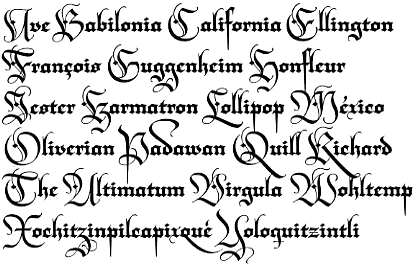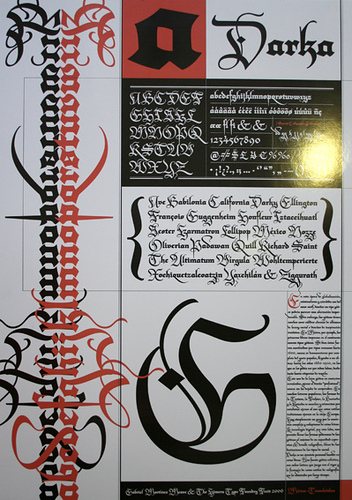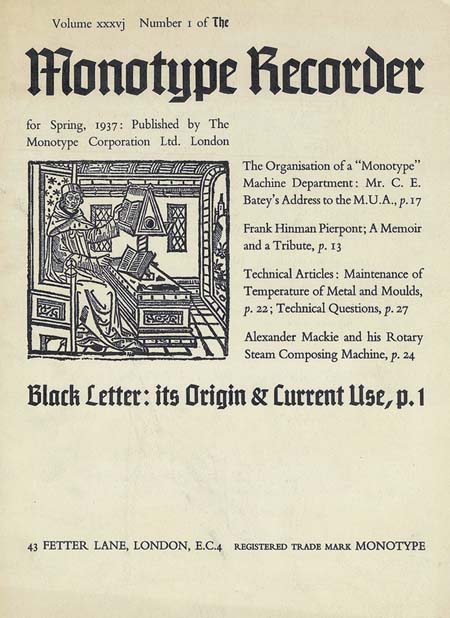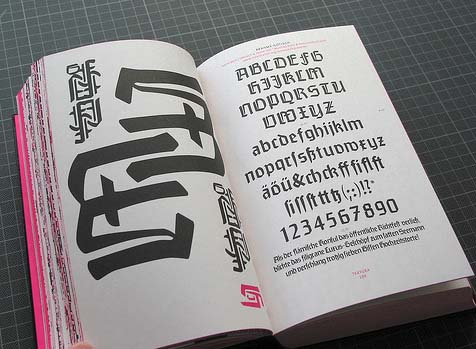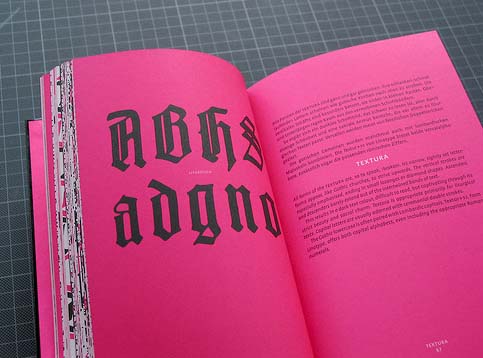
Fraktur - revivalismo
O Blackletter Revival: a Fraktur pelos quatro cantos do mundo...
A Blackletter sempre teve o seu protagonismo no mundo tipográfico britânico...
Blackletter Monotype Recorder
Monotype Recorder, 1937, sobre o uso da Blackletter
Nos últimos anos, temos assitido a um verdadeiro revivalismo da letra Fraktur. Especialmente devido a impulsos oriundos dos EUA e do México. Diseño Kimera propõe a fonte Darka - uma bela reincarnação da velha Fraktur no Novo Mundo:
Fraktur mon amour
Judith Schalansky. Fraktur mon Amour. 648 Seiten mit über 300 Frakturzeichensätzen und Schmuckbuchstaben aus insgesamt 644 Fonts
Como usar fontes Fraktur?
Bibliografia
• Anderlind, J. Deutschschrift, nicht Lateinschrift dem deutschen Volke. Berlin, 1911. Polémica pró-Fraktur, de cariz nacionalista.
• Brage, Hermann. Geschichte der Buchdruckerkunst. Leipzig, 1940. História da Imprensa.
• Bauer, Konrad F. Zur Geschichte der Unger-Fraktur. Gutenberg Jahrbuch, 1929.
• — Leonhard Wagner, der Schöpfer der Fraktur. Ein Beitrag zur Geschichte der deutschen Schrift. Frankfurt / Main, 1936.
• — Von der Zukunft der Schrift. Frankfurt / Main, 1966.
• Bissels, Paul. Humanismus und Buchdruck. Nieuwkorp, 1965.
• Chappel, Warren. A Short Story of the Printed Word. New York, 1970.
• Clauss, H. Die Schwabacher Schrift in Vergangenheit und Gegenwart. Leipzig, 1916.
• Crous, Ernst. Dürer und die Schrift. Berlin, 1923.
• Doede, Werner. Schön schreiben, eine Kunst. Johann Neudörffer und seine Schule im 16. und 17. Jahrhundert. München 1957.
• Ehmcke, Fritz Helmuth. Die drei Ausdrucksformen der deutschen Schrift: Textur - Schwabacher - Fraktur. Leipzig, 1912.
• Flood, J.L. Nationalistic currents in early German typography. The Library, 6a série, 15, 2, pp. 125-41. 1993.
• Fichtenau, Heinrich. Mensch und Schrift im Mittelalter. Wien, 1946. Grafias medievais.
• — Die Lehrbücher Maximilians I und die Anfänge der Frakturschrift. Hamburg, 1961.
• Franck, Paul. Schatzkammer allerhand Versalien, Nürnberg, 1601.
• Fugger, Wolfgang. Ein nützlich und wolgegrundt Formular manncherley schöner schriefften. Nürnberg, 1553. Fac-símile do manual de caligrafia de Fugger, com introd. de Fritz Funke. Leipzig, 1958.
• — A practical and well-grounded formulary for divers fair hands. Fac-símile da edição de 1597/1605, tradução de Frederick Plaat, introdução de Harry Carter. London, 1960.
• Heiderhoff, Horst. Antiqua oder Fraktur? Zur Problemgeschichte eines Streits. Polygraph Verlag. Frankfurt am Main, 1971. Importante ensaio sobre aopção histórica da cultura alemã: Fraktur ou letra romana?
• — Dürers Beitrag zur technischen Reproduzierbarkeit der Schrift. Lynotype-Post, 73. Frankfurt am Main, 1971.
• Goldschmidt, E.F. The Printed Book of the Renaissance. Type, Illustration, Ornament. Cambridge, 1950.
• Johnson, A.F. A History of the old English Letter Foundries. London, 1887.
• Kapr, Albert. Johann Neudörffer der Ältere, der grosse Schreibmeister der deutschen Renaissance. 48 Faksimilietafeln. Leipzig, 1956.
• — Fraktur. Form und Geschichte der gebrochenen Schriften.Verlag H. Schmidt, Mainz, 1993. A mais completa obra sobre as letras góticas e as suas derivadas tipográficas.
• — Deutsche Schriftkunst. Dresden, 1955.
• Kautzsch, Rudolf. Die Entstehung der Frakturschrift. Mainz, 1922.
• Klingspor, Karl. Über Schönheit von Schrift und Druck. Frankfurt am Main, 1949.
• Knebel, Ernst. Antiqua oder Fraktur? Danzig, 1887.
• Ludwig, Alfred J. Antiqua oder Fraktur - eine alte Streitfrage. Der Druckspiegel, Nr. 7. Stuttgart, 1968.
• Mori, Gustav. Luthers Beziehung zum Buchdruck. Berlin, s. data.
• Newton, Gerald. Deutsche Schrift: The Demise and Rise of German Black Letter. In: German Life and Letters 56 (2), 183-211. 2003. O autor é docente na Universidade de Sheffield.
• Oslender, Alfons. Herkunft und Bedeutung der Antiqua und Fraktur im Werke Albrecht Dürers. Dissertação. München, 1924.
• Renner, Paul. Antiqua oder Fraktur? In: Das moderne Buch. Lindau, 1948. O autor da Futura pronuncia-se sobre a opção.
• Schalansky, Judith. Fraktur mon Amour. Verlag H. Schmidt, Mainz, 2005. 648 páginas com exemplos de mais de 644 fontes Fraktur. CD-ROM com 130 fontes. Uma substancial declaração de amor à Fraktur.
• Uchelen, Croiset van. Vive la Plume! Trabalhos caligráficos de mestres, como Félix van Sambix, Jan van der Velde e Cornelis Dircksz Boissens. Universiteitsbibliothek Amsterdam. Catálogo da Exposição.
• Updike, Daniel Berkeley. Printing Types. Cambridge, 1927.
• Wagner, Leonard. Proba centum scripturarum una manu exaratarum 1507. Livro de estilo com mais de 100 caligrafias, algumas da invenção de Wagner. Fac-símile. Carl Wehmer Verlag. Frankfurt am Main, 1963.
• Willberg, Hans Peter. Vom falschen Image der Fraktur. Verlag H. Schmidt. Mainz, 1993.